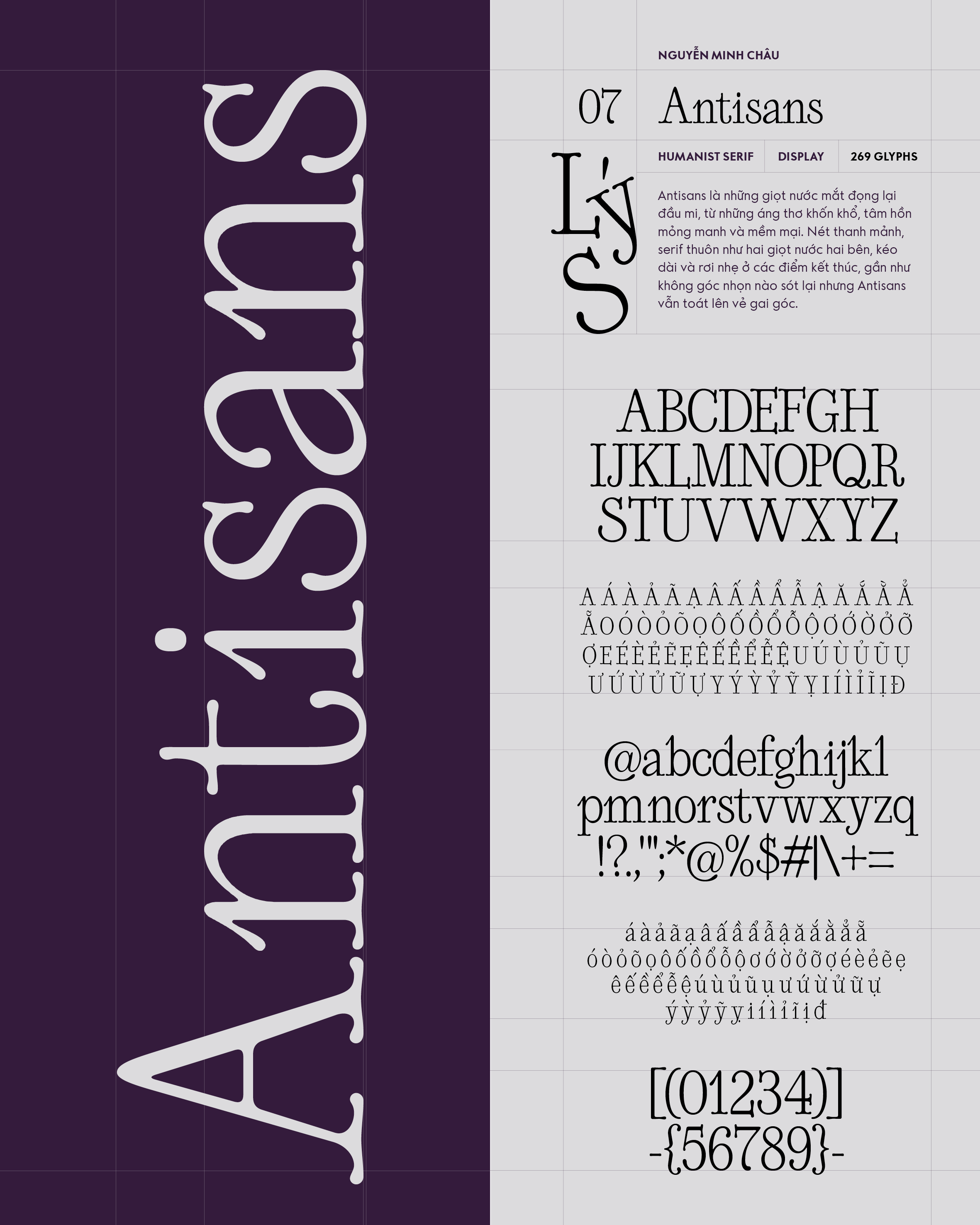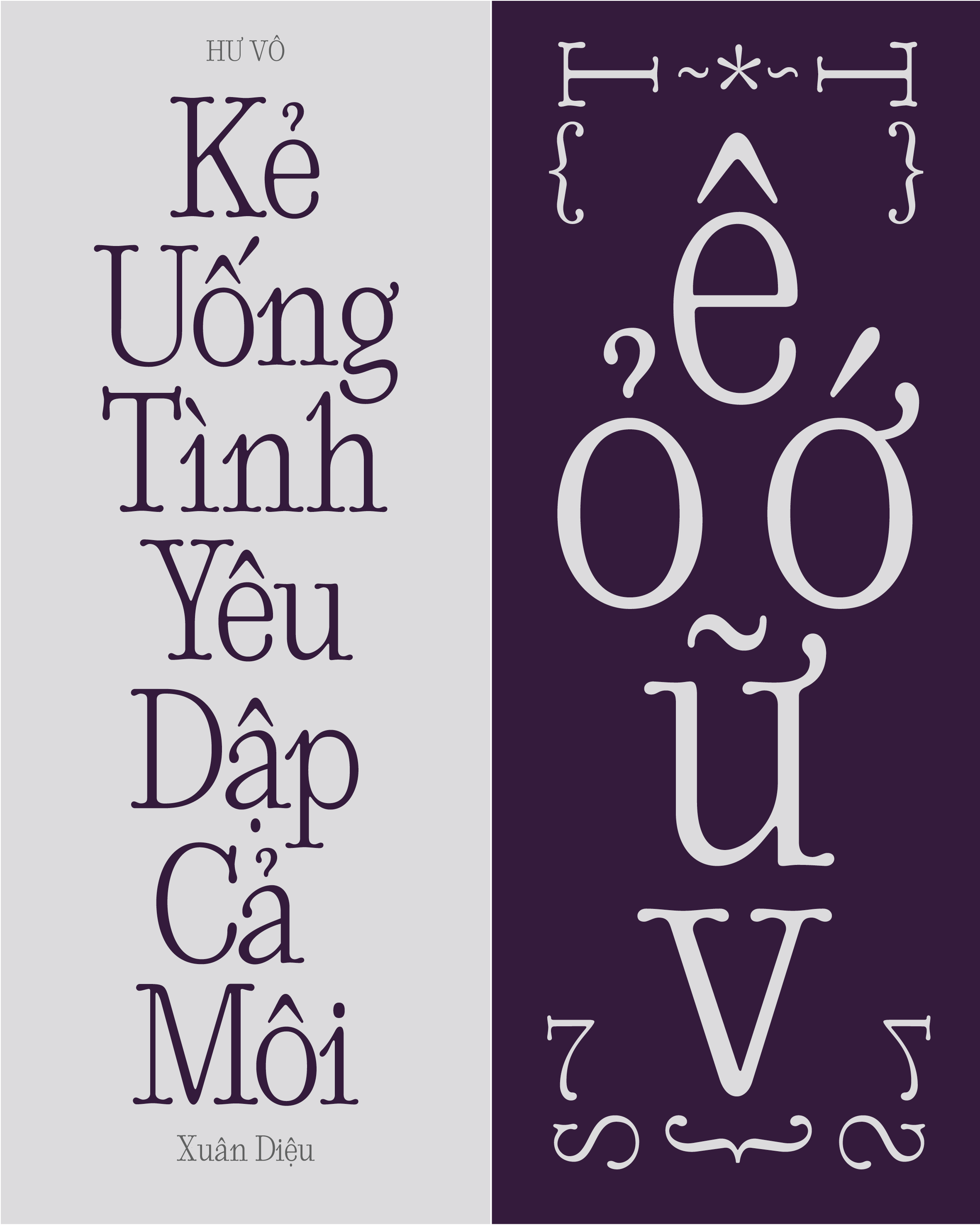
Antisans
Về Antisans: Antisans là những giọt nước mắt đọng lại đầu mi, từ những áng thơ khốn khổ, tâm hồn mỏng manh và mềm mại. Nét thanh mảnh, serif thuôn như hai giọt nước hai bên, kéo dài và rơi nhẹ ở các điểm kết thúc, gần như không góc nhọn nào sót lại nhưng Antisans vẫn toát lên vẻ gai góc.
Contemporary Serif
Display
Nguyễn Minh Châu